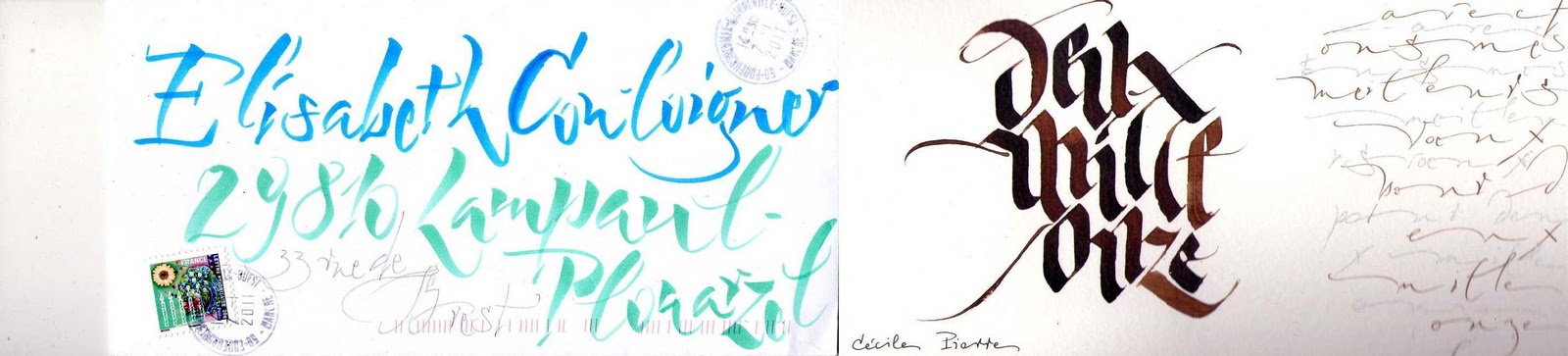
Meilleurs voeux 2011, c'est le dernier jour de souhaits.
Ainsi que je disais hier, au fur et à mesure, les cartes et les enveloppes ont évolué. J'ai fini par des enveloppes en organdi, qui laissent transparaître le contenu.
J'ai parfois joué avec les fils de couture qui dépassent de la carte, sur certaines enveloppes je les ai associés à des écritures. Jeu de liens entre les lignes des branches, des écritures, des fils, convergence vers un même sens plastique.
Et le support à la trame fine accueille le pinceau plat avec une évidente bonne volonté.
Bonne année à toutes et tous !!!
Meilleurs voeux 13.
Évocation du fouillis des branches par transparence et superposition.
J'ai créé un un album Picasa qui rassemble une partie des cartes de voeux que j'ai expédiées cette année. Au fur et à mesure des jours, de nouvelles idées sont arrivées et vous pouvez voir l'évolution du travail.
Voeux reçus 2011 - 8.
Très originaux, les vœux d'Alain, un de mes élèves.
Zagriff, l'Elisabeth toulonnaise m'envoie les couleurs du sud.
Meilleurs voeux 12.
Pour une destinataire qui m'expédie toujours des merveilles. (faites descendre le curseur une fois sur la page).
Voeux 2011 : le contenant a son importance.
Le plaisir de l'art postal commence lorsque l'on aperçoit l'enveloppe dans la boîte aux lettres au milieu du courrier et des prospectus. Je me dépêche alors de rentrer pour l'ouvrir proprement. L'extérieur est souvent promesse d'un beau contenu, surtout en cette période de vœux. Je suppose que mes correspondants réagissent de même.
En voici quelques-unes que j'ai récemment postées.
Et puis en voilà d'autres :
Meilleurs voeux 11.
Détail d'une des cartes de voeux : effet de transparence. Sous le voile la calligraphie est réalisée au pinceau pointu, à la gouache noire sur Ingres Butten.
Meilleurs voeux 10.
La calligraphie est réalisée à la plume Speedball. L'image imprimée provient d'une série de photos réalisées à l'entrée du château de Kergroadez.
Les visiteurs accèdent au château par une allée de chênes. J'ai fait une série de photos de ce fouillis de branches aux lignes puissantes. Puis je les ai retravaillées assez simplement. Pas de photoshop mais un petit xnview qui m'a permis de recadrer, passer en noir et blanc, jouer avec le contraste, la luminosité et le gamma.
Puis j'ai imprimé les photos par deux sur du A4 sur mon imprimante basique.
Stage Pierrelaye : Kitty Sabatier.
Le week-end dernier, je me suis rendue à Pierrelaye, au nord-ouest de Paris pour suivre un stage donné par Kitty Sabatier : " De la lettre à l'abstraction". La graveuse Joëlle Dumont nous a accueilli dans son atelier, un cadre extrêmement agréable.
Kitty nous a demandé de choisir une suite de lettres, (j'ai sélectionné 3 voyelles, une ascendante et une descendante en chancelière), à laquelle j'ai appliqué des transformations formelles -proposées par Kitty - variées sans souci de lisibilité bien sûr. La suite de la démarche consistait à combiner plusieurs de ces transformations sur un même motif. Nous sommes ainsi passés de la lettre à la composition.
Et pendant les pauses, je me suis reposée avec des exercices de composition photographique sur le bassin au poissons rouges du jardin.
J'ai rassemblé quelques images de mes recherches dans un diaporama à gauche de ce blog, visible aussi ici.
Exposition "Traits d'union" Paris 10ème : des images.
Je vous parlais il y a quelques jours de l'exposition "Traits d'union à la mairie de Paris 10ème.
Sur FB, Stéphane Alfonsi signale un site qui montre des images de l'expo. C'est de là que provient l'image ci-contre. Cela donne envie, non?
Allez voir ici, sur Typographisme.
Voeux reçus 2011 - 6.
Des peintres ....
Un dessin original d'Odile, connue aussi sous le nom d'Od'la. (Si vous avez un compte Google vous pouvez admirer ses cabanes ici. Essayez quand même sans compte google).
Un autre dessin original, du peintre Jean-Pierre Guiriec.
....Et des calligraphes :
Gérard Guerry
Callie (visitez son blog)
Un dessin original d'Odile, connue aussi sous le nom d'Od'la. (Si vous avez un compte Google vous pouvez admirer ses cabanes ici. Essayez quand même sans compte google).
Un autre dessin original, du peintre Jean-Pierre Guiriec.
....Et des calligraphes :
Gérard Guerry
Callie (visitez son blog)
Voeux reçus 2011 - 5
Stéphane Alfonsi : son myspace.
Les vœux de Skrivañ, l'association de calligraphie dont je suis membre. Merci Marie-Louise et Renée B.
Divers documents et objets anciens témoigneront de l'histoire de l'écriture.
Et cerise sur le gâteau , David Lozach a réalisé une vidéo sur l'évènement.